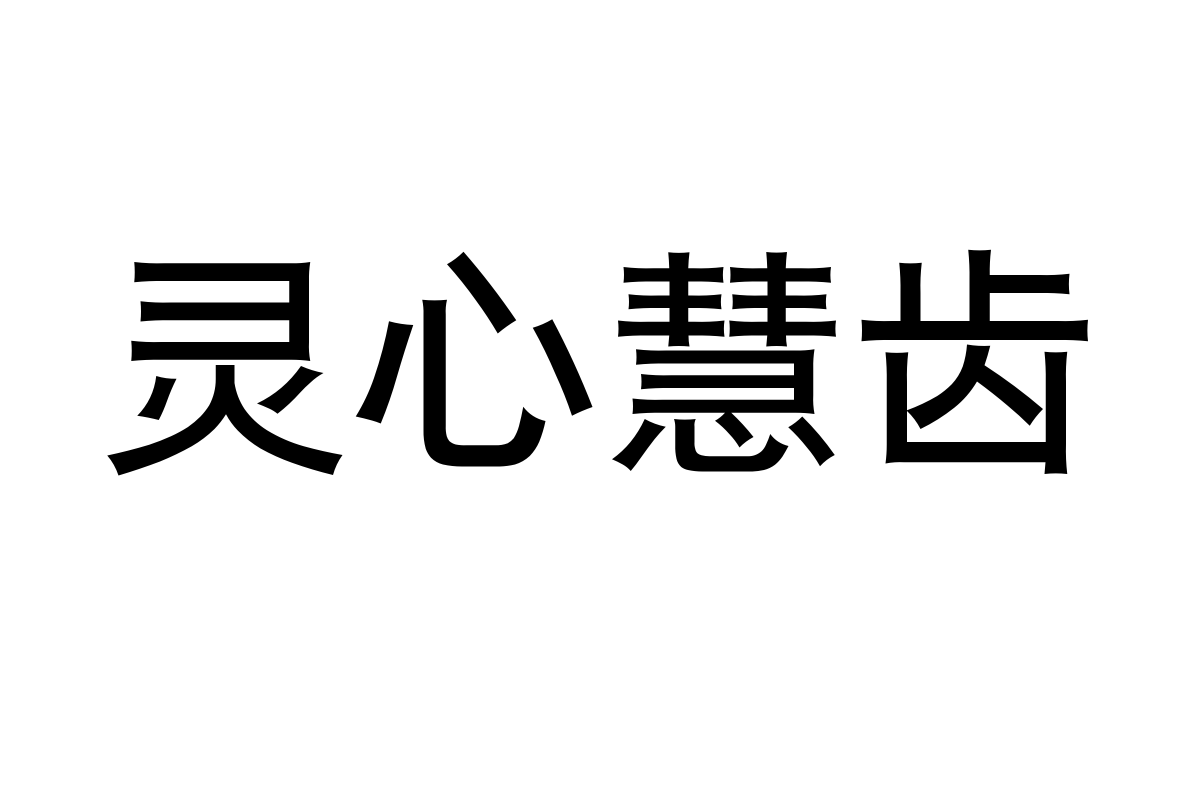
汉仪君黑-65是一款具有独特风格的中文字体,它以其简洁而优雅的设计风格赢得了广大用户的喜爱。这款字体采用了现代简约的设计元素,使得整体看起来更加干净利落。同时,它的笔画粗细适中,既不会显得过于粗犷,也不会过于细腻,给人一种平衡而舒适的视觉感受。
在字形结构上,汉仪君黑-65保持了一定的规整性,每个字都呈现出一种流畅的线条感。这使得整个字体看起来既有力度又不失柔和,适合用于各种需要强调文字美感的场合。
此外,这款字体还具有一定的可读性。虽然它采用了简洁的设计手法,但每个字的结构和笔画都经过精心设计,使得阅读起来既不会感到吃力,又能保证信息的准确传达。
总的来说,汉仪君黑-65是一款非常适合现代设计需求的中文字体。无论是用于网页设计、平面设计还是其他需要文字表达的场合,它都能展现出其独特的魅力和实用性。